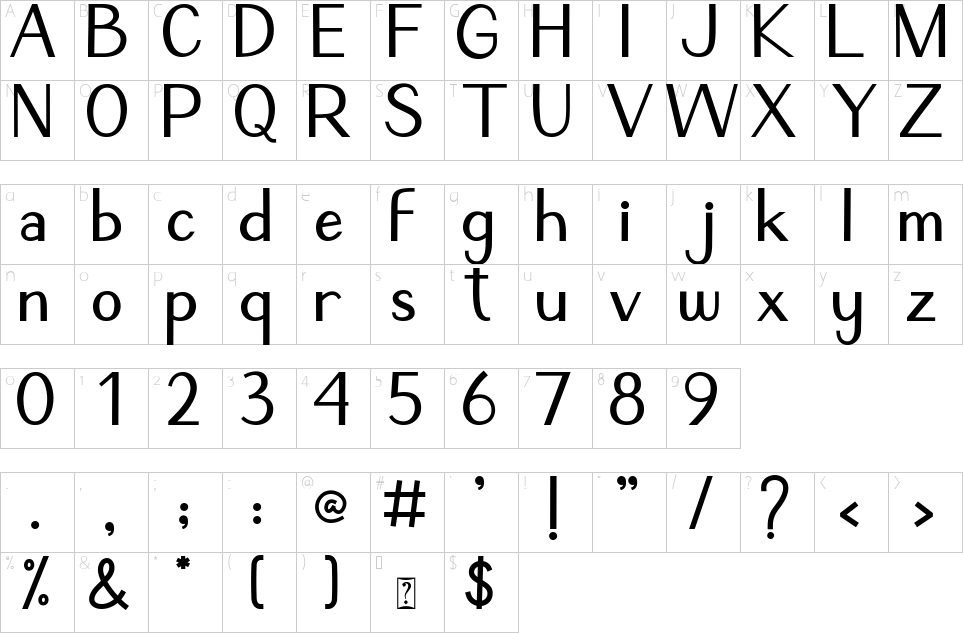
A Marqana é uma fonte de design moderno e elegante, ideal para criar designs de alta qualidade sem ter que gastar. Ela foi criada pela AEN Creative Studio e já foi baixada mais de duas mil vezes. Esta fonte é perfeita para uso em sites, revistas e editoriais de blog, oferecendo um estilo clean e moderno que pode ser facilmente personalizado. O Marqana tem uma variedade de opções de tamanho e estilo, desde linhas finas e elegantes até bold e vibrantes. Se você está buscando uma fonte de alta qualidade que se destaca e é fácil de usar, a Marqana é uma ótima escolha.